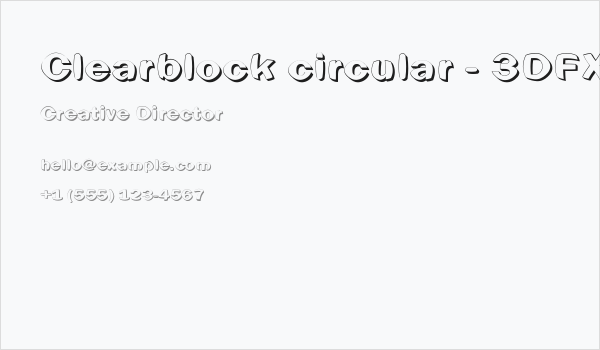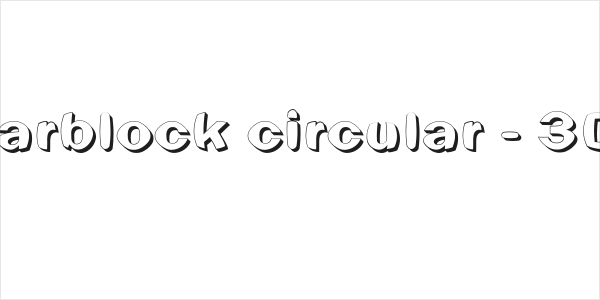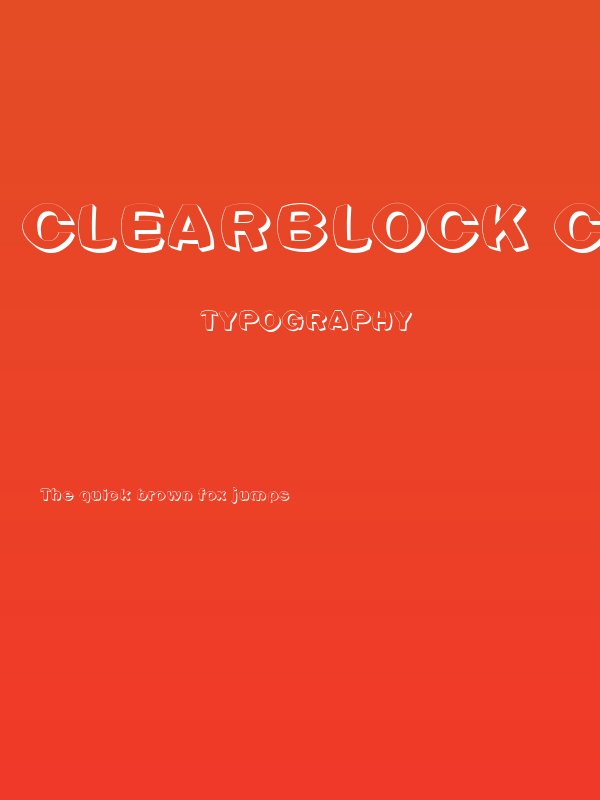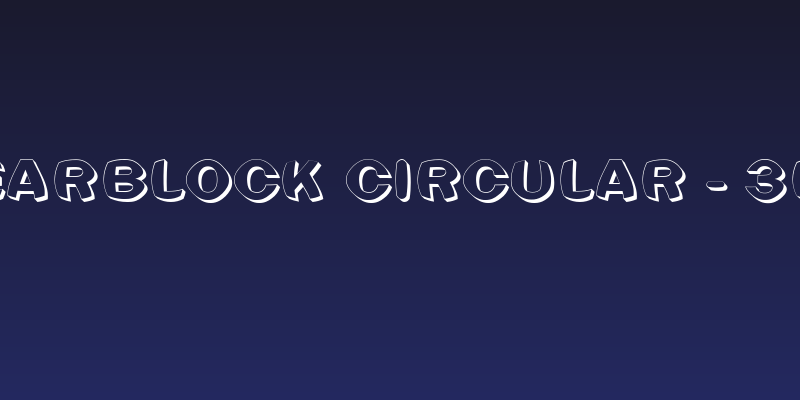
Clearblock circular - 3DFX Font
✎ Outline
| Progetti proposti | Ideal for children's book covers, playful branding, posters, and eye-catching headlines. |